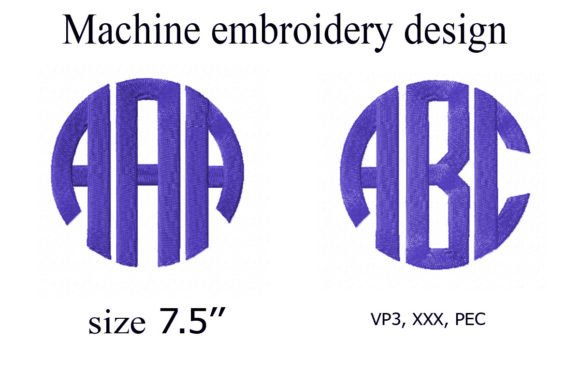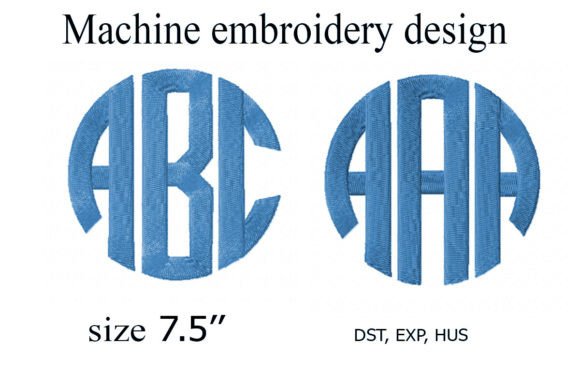
Circle Monogram
適切なデザイン要素を見つけるのは難しい場合がありますが、Circle Monogramは作品を即座に引き立てる優れたコレクションを提供します。
精密に作られたCircle Monogramは、クリーンなベクター、滑らかなタイポグラフィ、そして安心のための商用ライセンスを提供します。
POD(オンデマンド印刷)製品、結婚式の招待状、またはソーシャルメディアのグラフィックを作成している場合でも、Circle Monogramは理想的です。